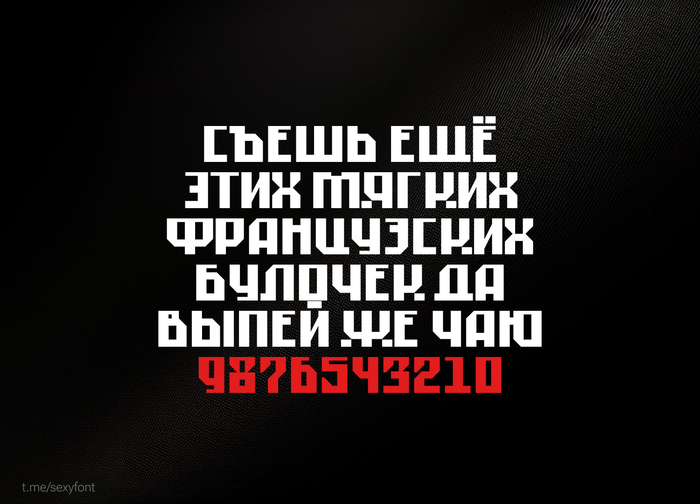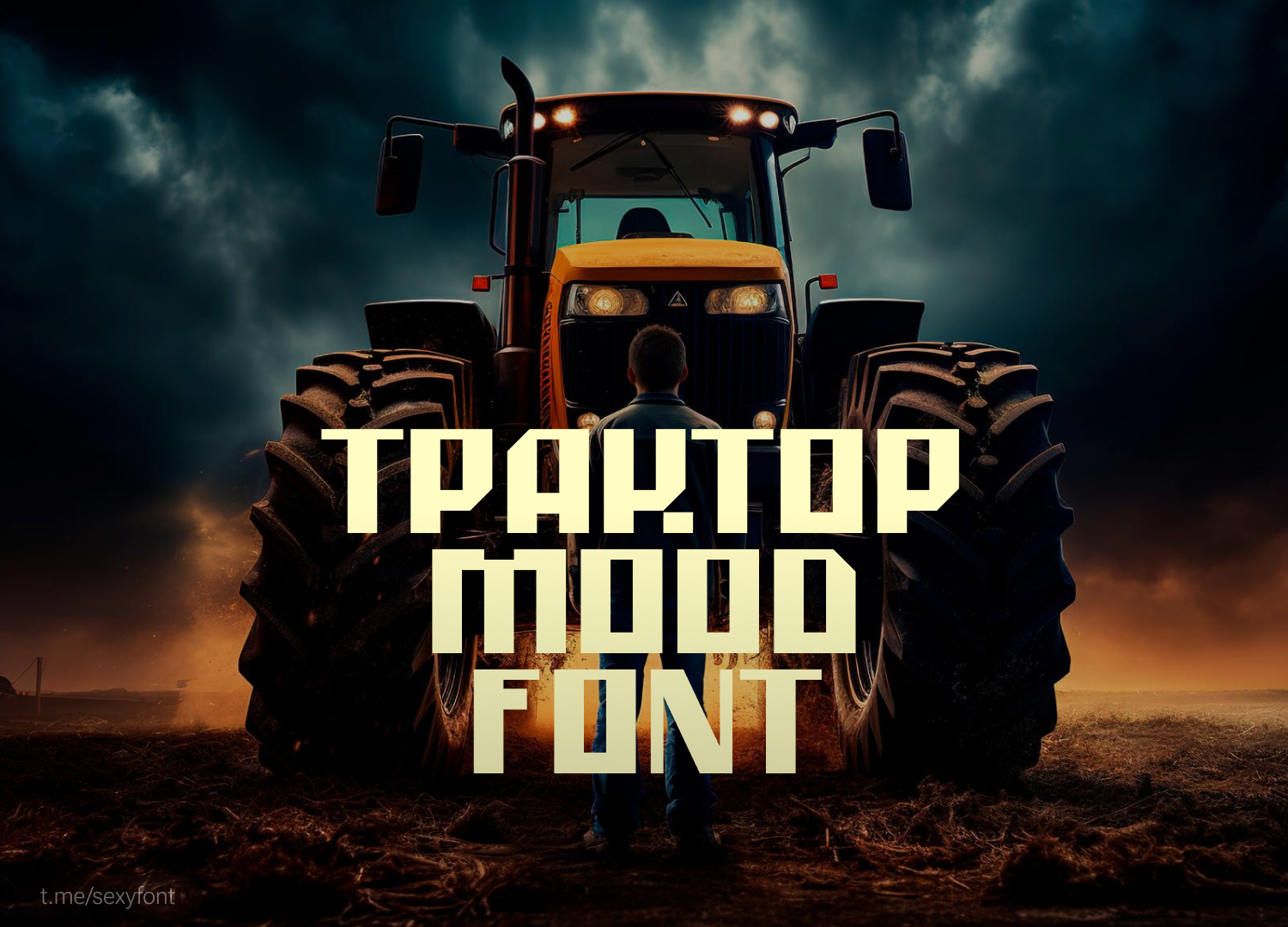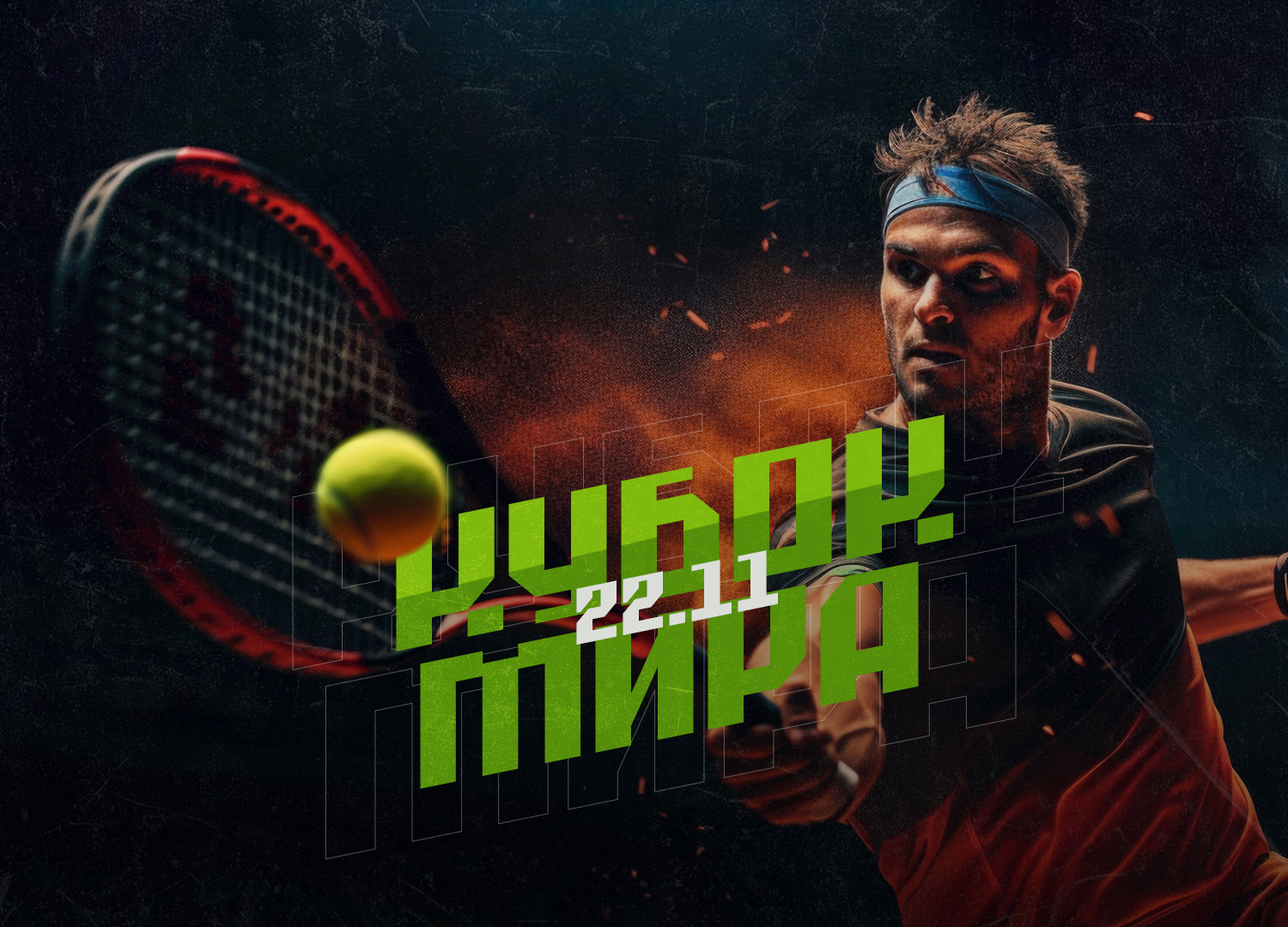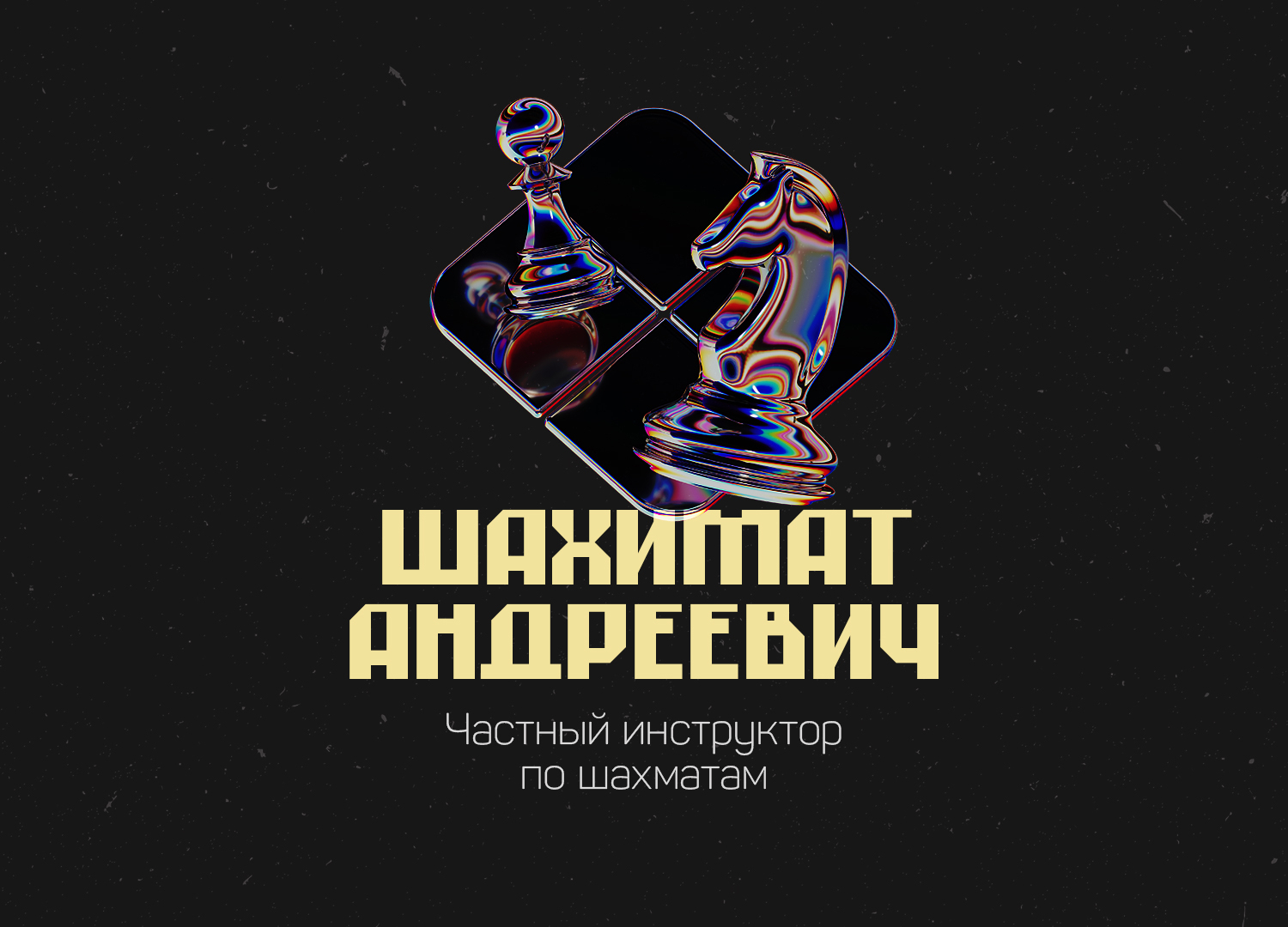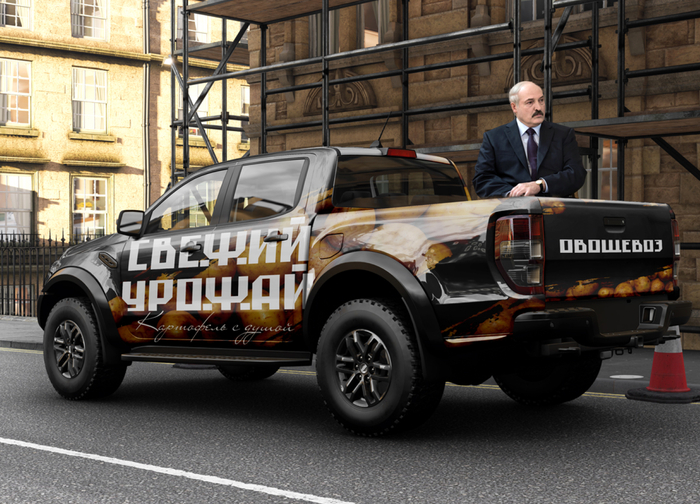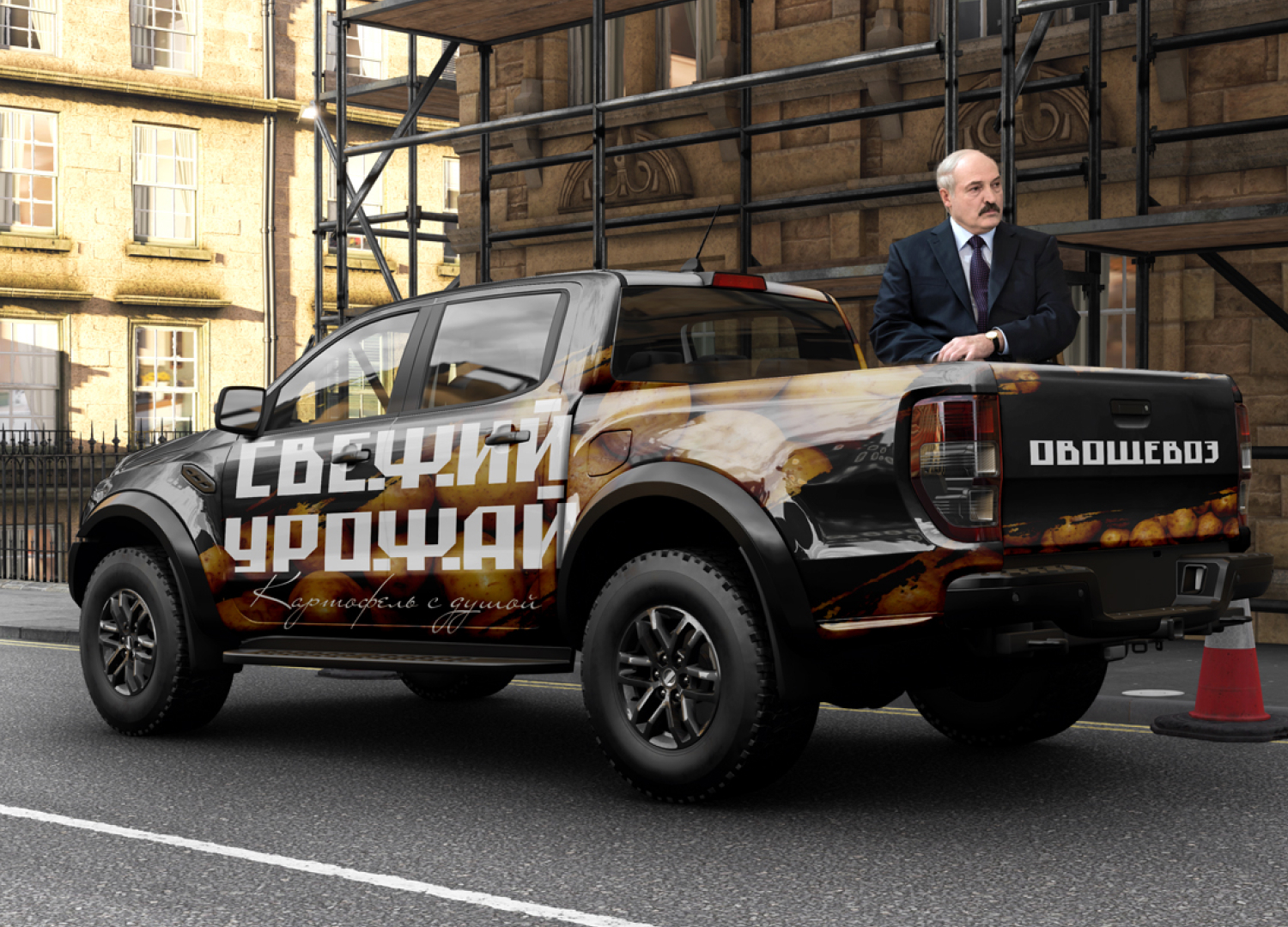
Шрифт Traktor. Кириллица
По полям, по полям... Traktor Mood едет к нам. Мощный, смелый акцидентный шрифт. Использовать только для коротких заголовков.